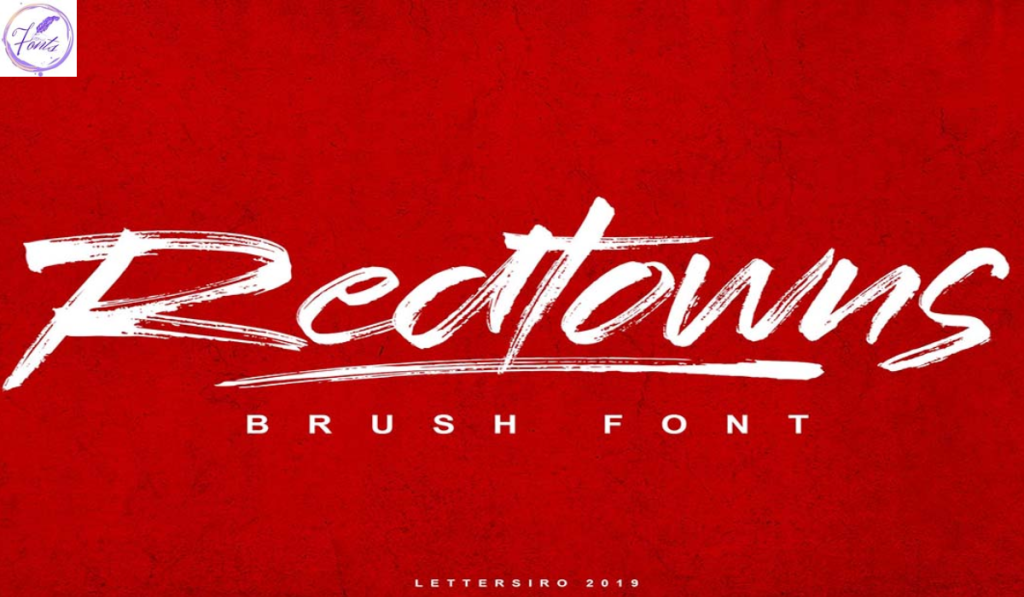
Font chữ bút lông việt hóa
Tác giả: Lettersiro
Bộ Font: Redtowns
Phân loại: cá tính, độc đáo, viết tay
Kiểu chữ: script, brush
font chữ bút lông là một trong những bộ font sáng tạo và nghệ thuật nhất, mang đến cho người dùng cảm giác tự do và phóng khoáng. Được thiết kế vào năm 2021 bởi Lettersiro, font này nhanh chóng trở thành lựa chọn yêu thích của nhiều nhà thiết kế và người dùng trên toàn thế giới. Với nét chữ mô phỏng theo phong cách viết tay bằng bút lông, font chữ bút lông mang đến sự mềm mại và tự nhiên, giúp các thiết kế trở nên sống động và độc đáo hơn.
Đánh giá font chữ bút lông
font chữ bút lông nhận được rất nhiều phản hồi tích cực từ cộng đồng thiết kế. Nhiều người dùng đánh giá cao sự chân thực và sinh động mà font này mang lại cho các dự án của họ. Các đường nét tự nhiên, uyển chuyển giúp font này trở nên lý tưởng cho các thiết kế thiệp mời, poster, và các tác phẩm nghệ thuật. Bên cạnh đó, font chữ bút lông còn hỗ trợ đầy đủ ký tự tiếng Việt, giúp bạn dễ dàng sáng tạo và biến hóa trong các văn bản và thiết kế mà không gặp bất kỳ trở ngại nào.